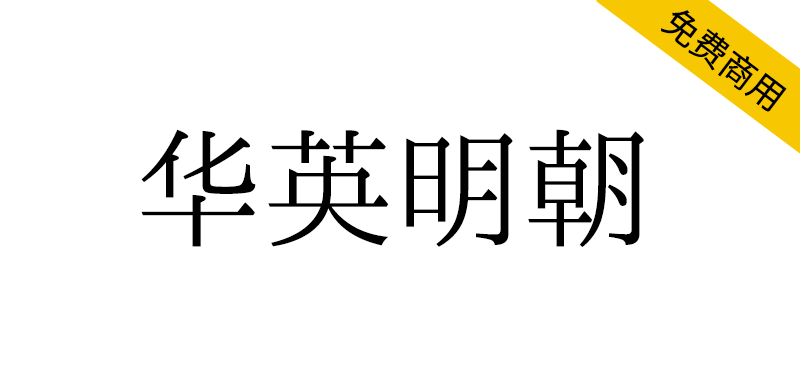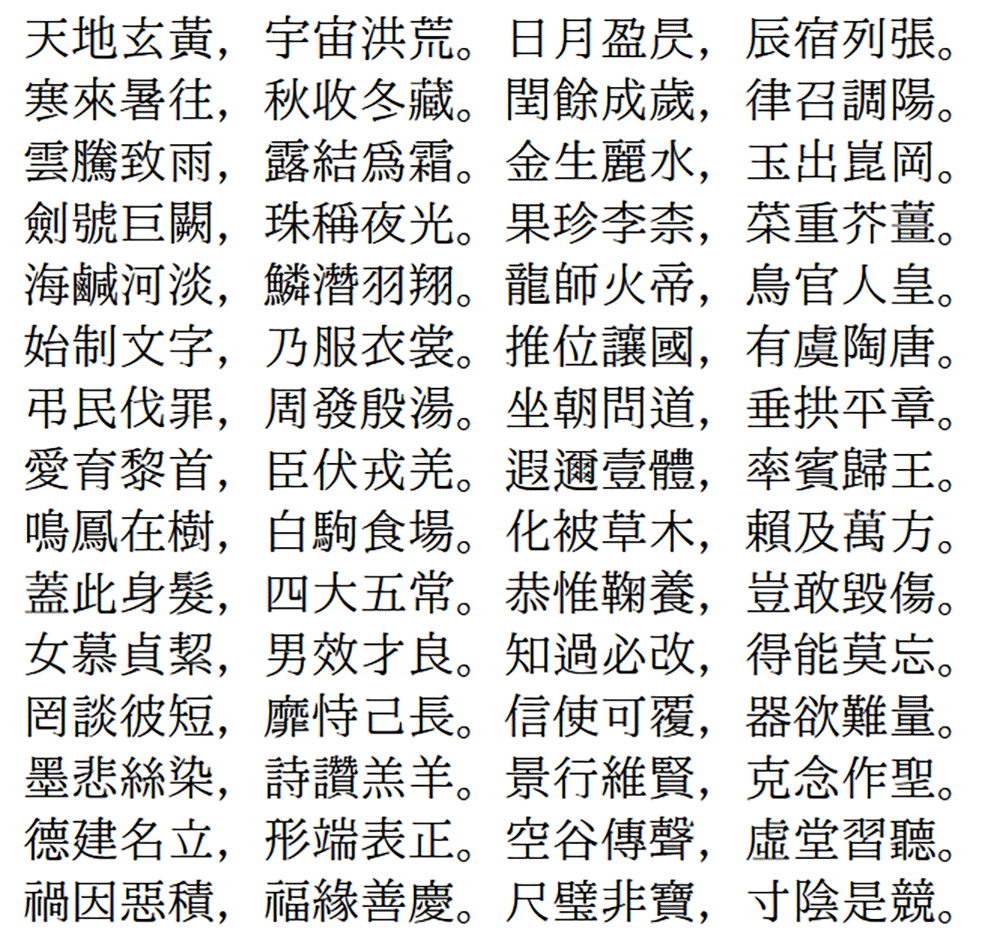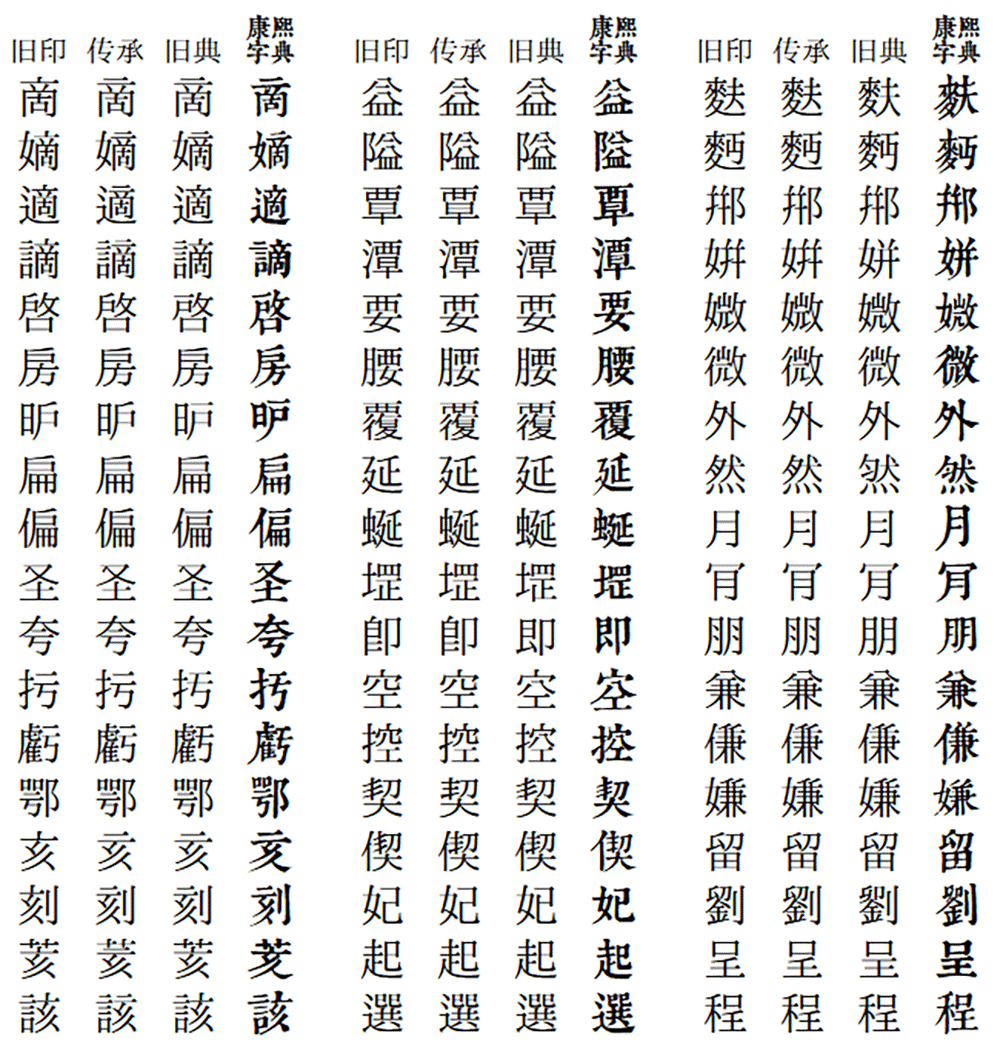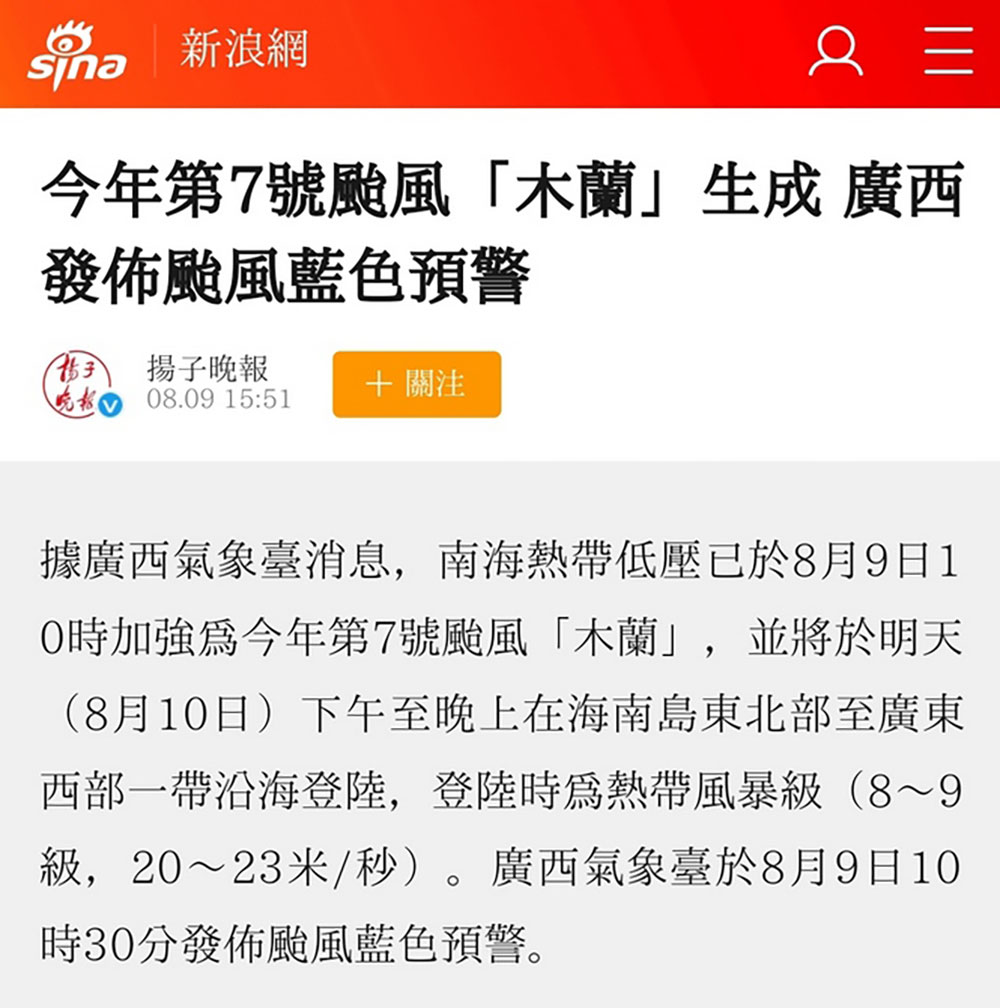
华英明朝(Huaying Mincho)是一套基于 IPAmj明朝 的衍生字体,拥有传承字形、旧字形风格的中文字体。华英明朝共提供 3 种字形风格,并带有符合 IVD_Charts_Moji_Joho 标准的异体选择器。
○ 华英明朝旧印体:旧印刷体,字形接近旧版Windows新细明体。
○华英明朝传承体:传承字形版,综合参考了包括《康熙字典》在内的经典旧字形资料。
○华英明朝旧典体:接近《康熙字典》中的字形,并保留古籍中汉字部件变化不一的特点。
○华英明朝繁体:在传承体的基础上制作,简入繁出的字体。通过使用字体的OpenType 技术,可根据文字的属性动态匹配一简多繁的情况。